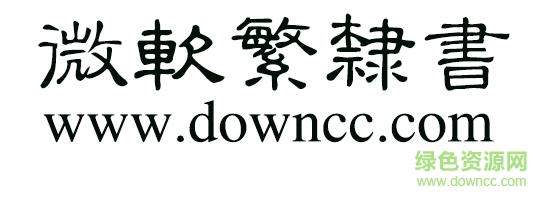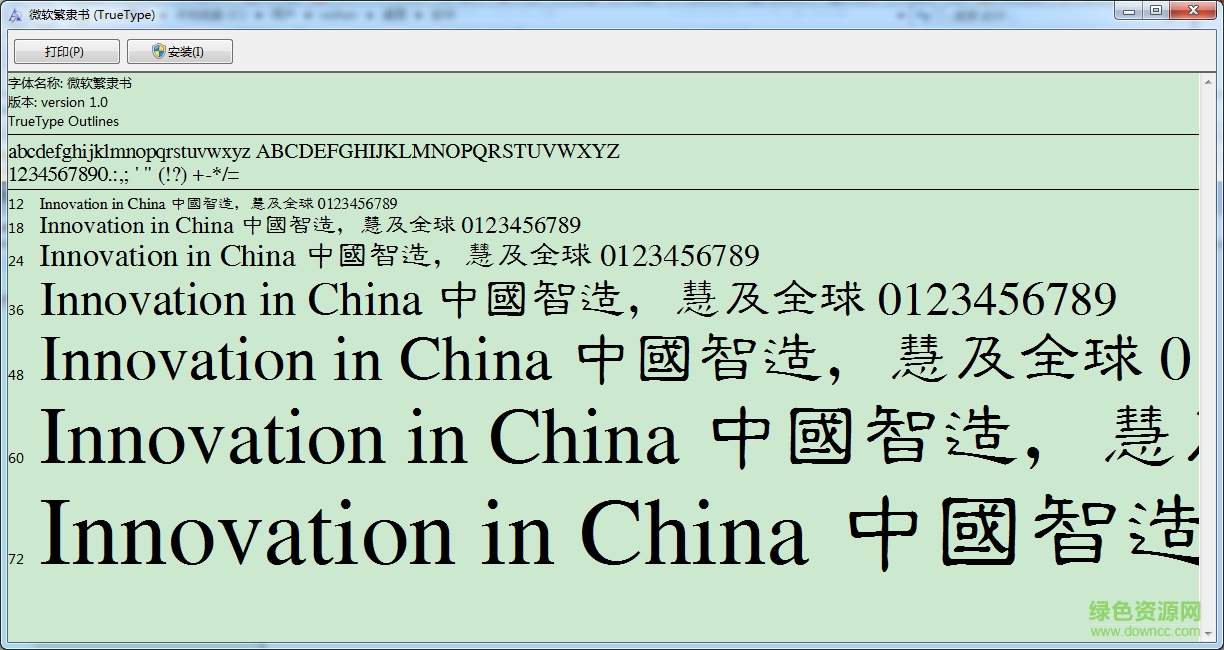
微軟繁隸書字體是由微軟推出的一個免費(fèi)字體。這款字體兼容多種主流系統(tǒng)環(huán)境。微軟繁隸書字體主要應(yīng)用于平面設(shè)計、印刷排版等場景!需要的用戶快來拿走吧。
微軟繁隸書是一款非常漂亮的隸書風(fēng)格的繁體字體,這款字體書寫效果略微寬扁,非常適合于美工設(shè)計,喜歡的朋友歡迎來綠色資源網(wǎng)下載!